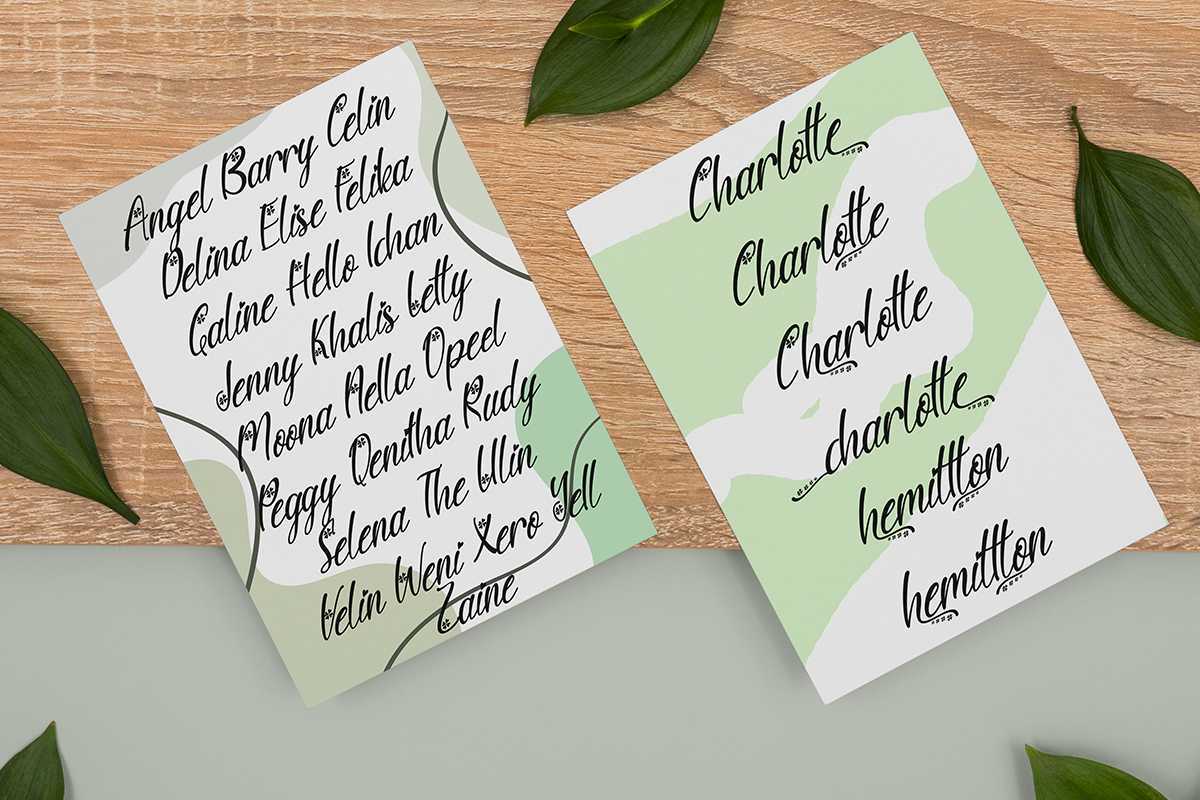
Sunny Love是一款精美的手写字体。这款字体配有精美的文字装饰。网页上的文字装饰非常简单,并且提供了良好的说明。这款字体适用于您的假期、夏天、春天、母亲节、父亲节、徽标、品牌、横幅、海报、印刷品、邀请、礼物、生日、婚礼、社交媒体、,Quotes and More.Sunny Love是一款精美的手写字体。这款字体配有精美的黑白字体装饰。手机上的标签非常方便,并提供了详细的说明。这款字体适用于您的假期、夏季、春季、母亲节、父亲节、徽标、品牌、旗帜、海报、印刷品、邀请、礼物、生日、婚礼、社交媒体、,引用和更多。